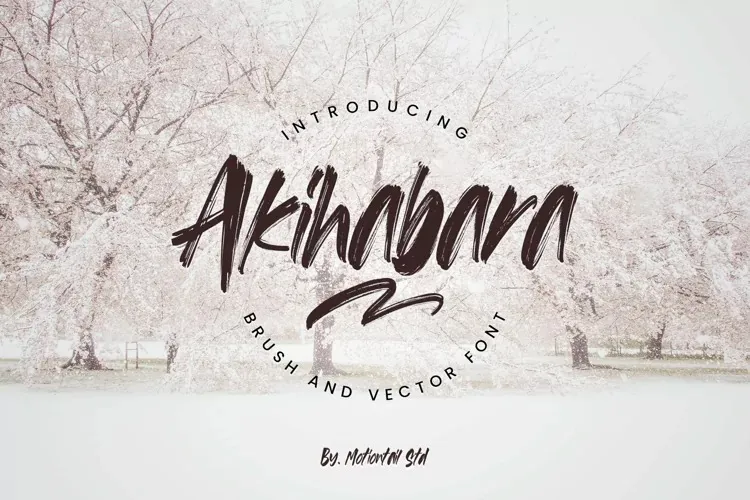
A Akihabara Font é uma criação meticulosa feita no aplicativo com a ferramenta pincel em estilo relaxado e criativo. Esta elegante fonte foi especialmente projetada para se adaptar a uma ampla gama de usos, desde nomecards até capas de revistas e banners. Seus traços detalhados são perfeitos tanto para criar logotipos sofisticados quanto para personalizar artigos em mangás ou roupas têxteis, como camisas ou blusas grafadas. A Akihabara Font também é ideal para artes de grande escala e cabe perfeitamente na maioria dos projetos digitais onde uma fonte com um toque único seja desejado. Com seu estilo criativo e sofisticado, ela encaixa-se perfeitamente para diversos aplicativos gráficos sem perder a qualidade ou o impacto visual que você deseja alcançar.